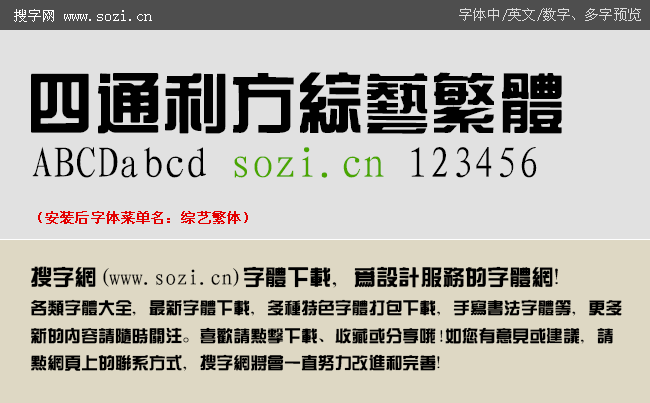
四通利方綜藝繁體
搜字網(wǎng)提供一款四通利方綜藝繁體下載。綜藝體是黑體的一種變體,也是藝術(shù)字的一種。特點(diǎn)是筆劃更粗,盡量將空間充滿。同時為了美觀,對拐彎處的處理較為圓潤。適用于廣告、報(bào)刊等的標(biāo)題及海報(bào)展板等設(shè)計(jì)場合使用。